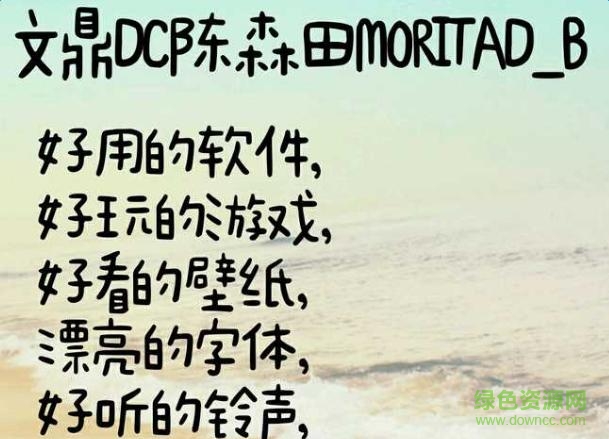
文鼎dc陳森田字體是一款非??蓯?ài)的藝術(shù)字體,這款字體比較趨向于非主流風(fēng)格,可以將文字變得比較有個(gè)性、有個(gè)性,喜歡這款字體的朋友可以來(lái)綠色資源網(wǎng)下載體驗(yàn)!
文鼎DC陳森田MORITA_B是文鼎科技與臺(tái)灣插畫(huà)家_陳森田一起合作開(kāi)發(fā)的手寫(xiě)字型。所有字體的內(nèi)容包含中文、英歐文、符號(hào)等,都是陳森田手寫(xiě)繪制,再由文鼎作字型數(shù)字化的開(kāi)發(fā)制作,將陸續(xù)推出繁中Big5字集、簡(jiǎn)中GB2312+ GB12345字集的TrueType字型。
這次推出的陳森田MORITA_B最大特色,所有的中文及英歐文,橫排或直排,都采用不同字寬的調(diào)和字設(shè)計(jì),每一個(gè)字都有不同的字寬,突顯了陳森田手寫(xiě)字的手感、Q感及溫度。